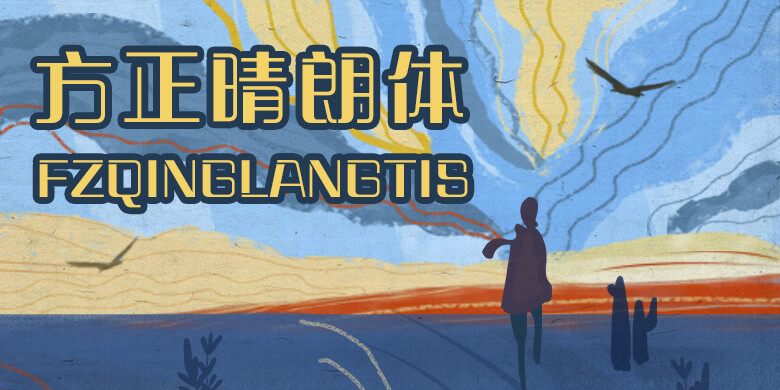
方正晴朗体-简繁-ExtraLight 系列,共16款简繁字体
方正晴朗体-简繁-ExtraLight
晴朗体创意灵感源于国外网上看见一个露天咖啡店的招牌“SUNNY CAFE”阳光咖啡店,字体很爽朗,充满阳光气息,所以命名为“晴朗体”。
晴朗体普遍每一个字只有两直划是粗的,其余横直都是细的,左边上下直角,右边上下是圆角,形成一个强烈对比,所以粗细的视觉很平均,不会有太重和太轻的感受,排版画刊更有舒服感觉,工整中还少许动感,美观齐整,空间分布平均,直划采用一粗一细的造型,配以特别的口型配合,是一款四平八稳严肃带小许动感,斯文大方,显示才华横溢的成功男女。它含8款不同粗细字体!
晴朗体适合金融、保险行业,汽车行业,投资行业,电子产品的商业宣传和包装设计!